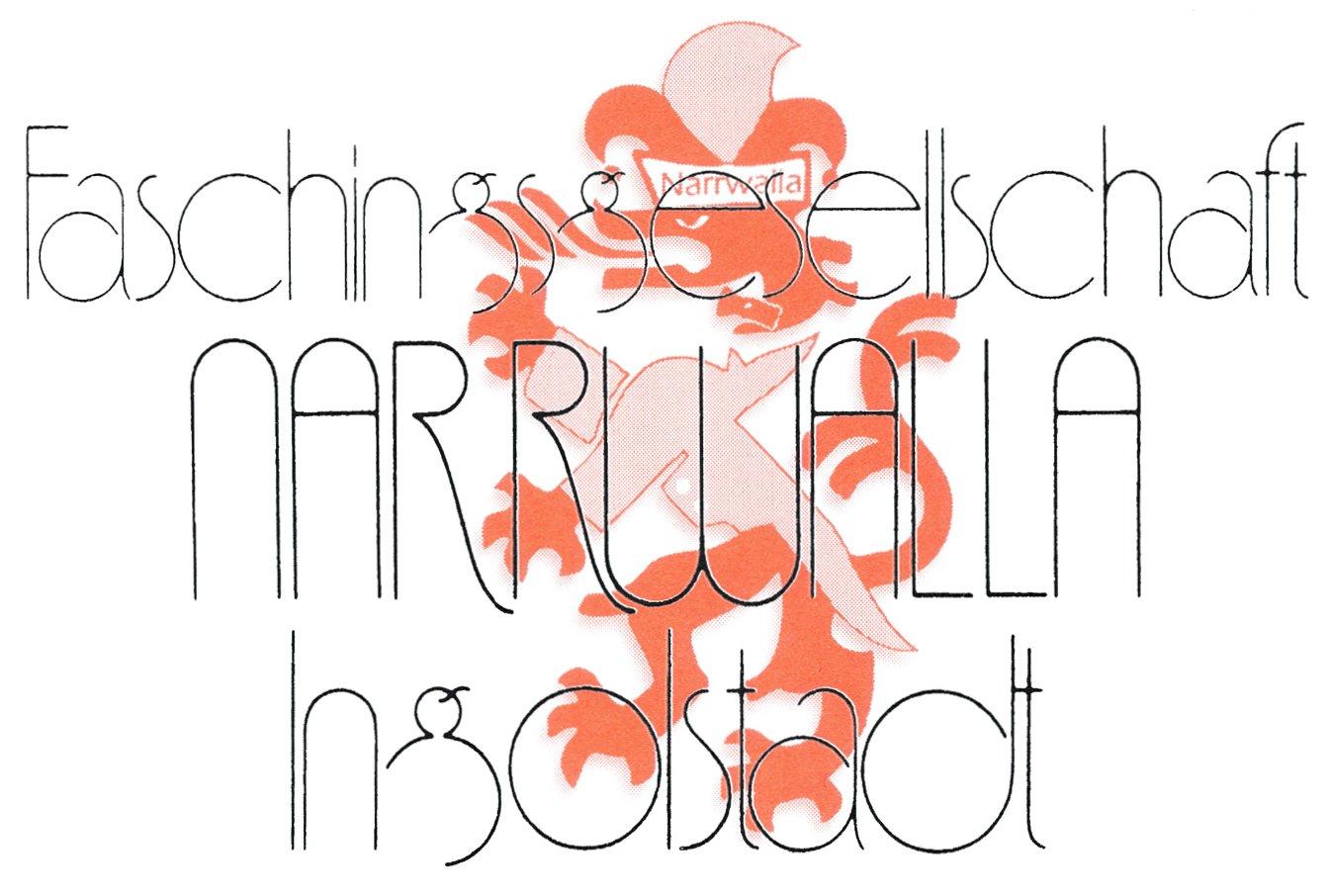
Welche Schriftart ist das ?
Dass die Schrift fetter ist, gefällt mir sogar ganz gut.
Kann durchaus sein, dass die ganzen Scannvorgänge das ganze dünner gemacht haben.